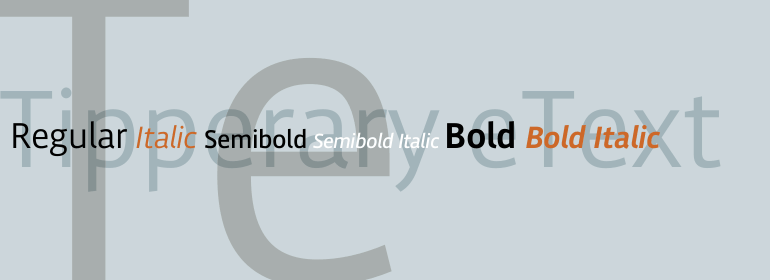
Tipperary™ eText
Tipperary™ eText,这款字体结构工整、笔画清晰,兼顾美观与易读性,适用于标题、正文、海报、包装、LOGO 等多种场景。字形优雅稳定,风格百搭耐看,适配日常排版与创意设计,让文字呈现更舒适、更具质感。Tipperary™ eText一笔一画,皆是细节,以均衡的比例、流畅的线条打造舒适视觉体验,字形端正大气,风格简约现代。无论是商业设计、品牌宣传还是日常排版,都能轻松驾驭,让文字更有格调与力量。Tipperary™ eText字体下载。